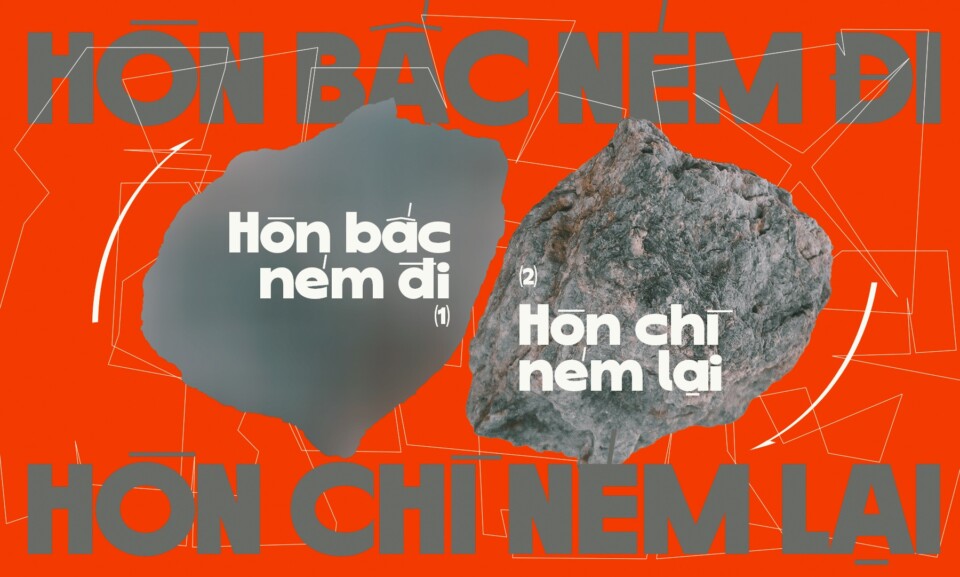
Bolero-esque Honora font – Đã có Tiếng Việt
Bolero-esque Honora font – Đã có Tiếng Việt: Sự kết hợp hoàn hảo giữa nét hoài cổ và hiện đại
Giới thiệu về bộ Bolero-esque Honora font – Đã có Tiếng Việt
Trong thế giới thiết kế đồ họa hiện nay, việc tìm kiếm một bộ Font Miễn Phí chất lượng và hỗ trợ đầy đủ ký tự đặc biệt luôn là ưu tiên hàng đầu của các bạn học sinh và thầy cô giáo. Đặc biệt, bộ Bolero-esque Honora font – Đã có Tiếng Việt nổi lên như một hiện tượng nhờ sự giao thoa tinh tế giữa phong cách Bolero cổ điển của Việt Nam và nét thanh lịch của phông chữ Honora hiện đại. Đây không chỉ đơn thuần là một công cụ soạn thảo, mà còn là linh hồn cho những tác phẩm nghệ thuật mang đậm dấu ấn thời gian nhưng vẫn đảm bảo tính ứng dụng cao trong học tập cũng như trình bày văn bản.
Tại sao nên chọn Bolero-esque Honora font – Đã có Tiếng Việt?
Lý do đầu tiên khiến bộ phông này trở nên phổ biến chính là khả năng hiển thị tiếng Việt xuất sắc. Nhiều bộ phông chữ quốc tế thường gặp lỗi hiển thị các dấu thanh như huyền, sắc, hỏi, ngã, nặng hoặc các chữ cái có mũ như â, ê, ô. Tuy nhiên, với phiên bản Bolero-esque Honora font – Đã có Tiếng Việt, mọi rào cản về ngôn ngữ đã được xóa bỏ hoàn toàn. Các ký tự được tinh chỉnh tỉ mỉ để giữ được sự đồng nhất về độ đậm nhạt và khoảng cách, giúp văn bản trở nên chuyên nghiệp và dễ đọc hơn bao giờ hết.
Ứng dụng thực tiễn của Bolero-esque Honora font – Đã có Tiếng Việt
Bộ phông chữ này cực kỳ phù hợp cho các dự án thiết kế mang tính hoài niệm hoặc cần sự trang trọng. Trong môi trường học đường, các em học sinh có thể sử dụng phông chữ này để làm bìa báo tường, thiết kế thiệp chúc mừng thầy cô hoặc trang trí cho các bài thuyết trình thêm phần sinh động. Những đường nét uốn lượn mềm mại nhưng chắc chắn của phông chữ gợi nhớ đến những tấm biển quảng cáo vẽ tay xưa cũ, tạo cảm giác thân thuộc và ấm áp cho người xem.
Lưu ý khi sử dụng phông chữ trong thiết kế
Mặc dù Bolero-esque Honora font – Đã có Tiếng Việt sở hữu vẻ đẹp độc đáo, người dùng cần lưu ý phối hợp với các phông chữ không chân (sans-serif) đơn giản cho phần nội dung dài để tránh gây mỏi mắt. Việc sử dụng phông chữ này làm tiêu đề chính sẽ tạo điểm nhấn cực kỳ mạnh mẽ, thu hút sự chú ý ngay từ cái nhìn đầu tiên. Đối với các thầy cô giáo, đây là công cụ tuyệt vời để tạo ra những tài liệu giảng dạy sáng tạo, giúp học sinh hứng thú hơn với bài học thông qua thị giác trực quan sinh động.